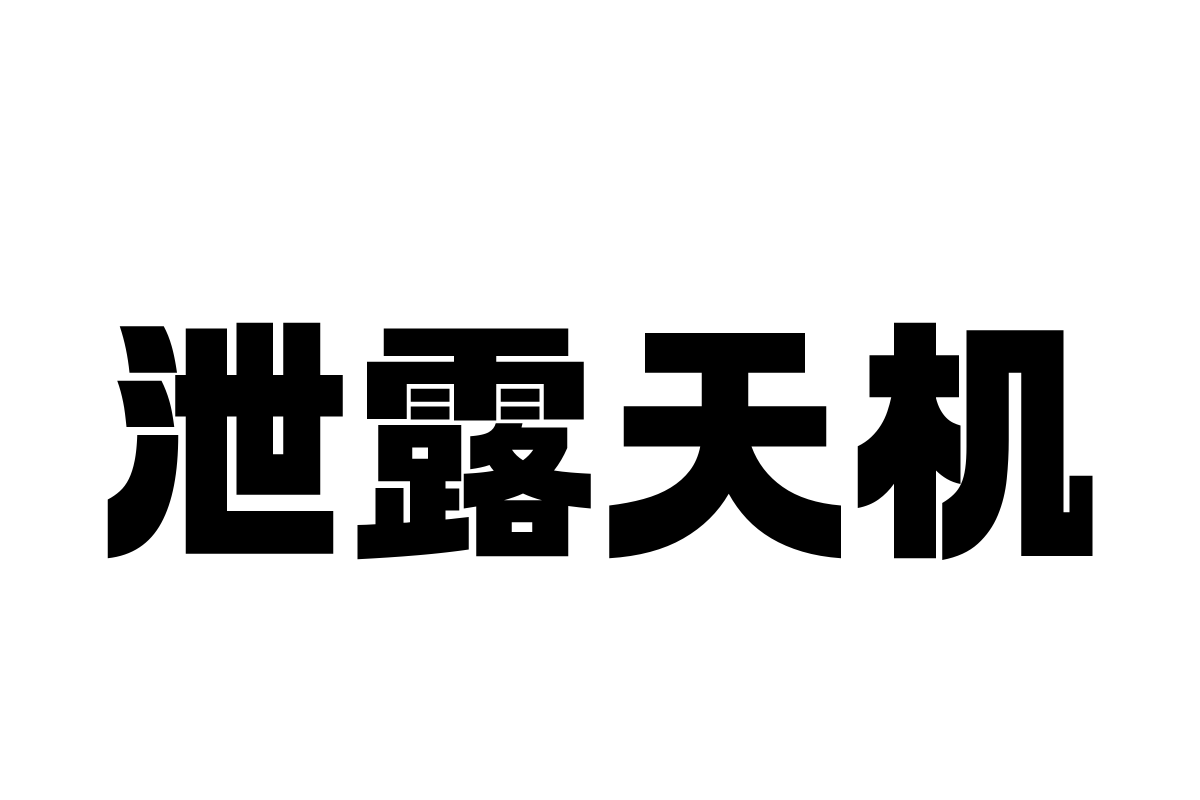
汉仪懒黑黑是一款现代简约风格的中文字体,具有独特的设计风格和良好的可读性。这款字体采用了简洁的笔画和流畅的线条,使得整体字形更加美观大方。同时,汉仪懒黑黑也注重细节的处理,使得每个字都显得精致而富有层次感。
该字体适用于各种应用场景,如标题、正文、广告、包装等,能够很好地融入不同的设计作品中。此外,汉仪懒黑黑还具有较高的可扩展性,可以根据需要进行个性化定制,满足不同设计师的需求。
总的来说,汉仪懒黑黑是一款非常实用的中文字体,无论是在商业还是个人项目中都能够发挥出色的表现。